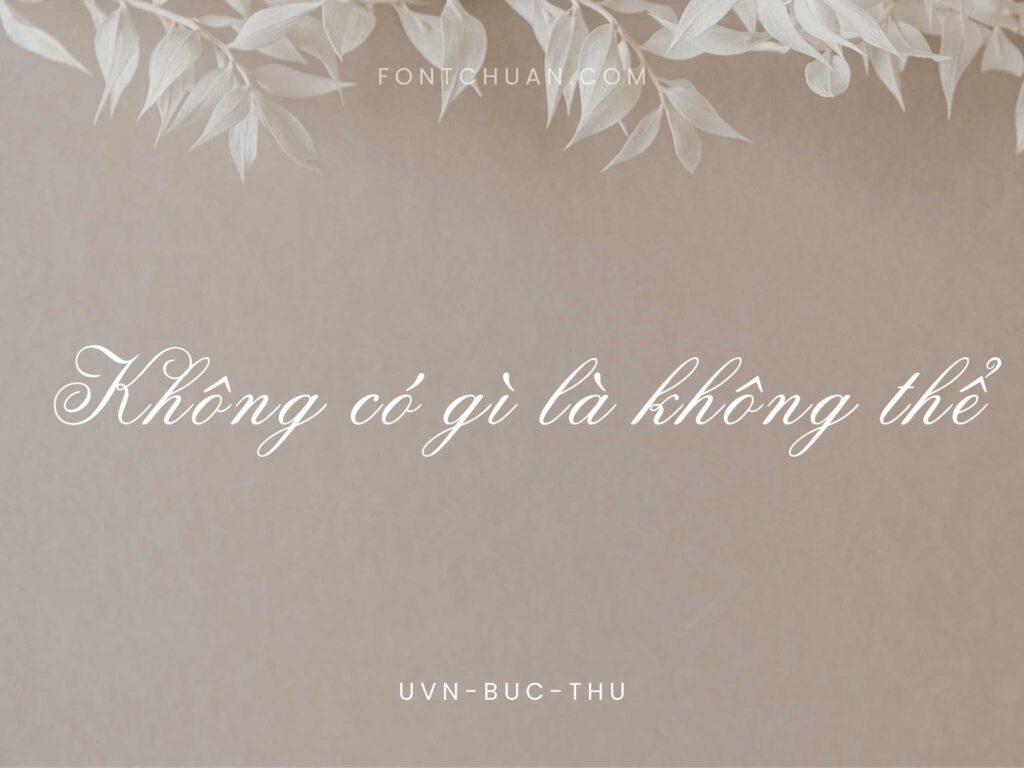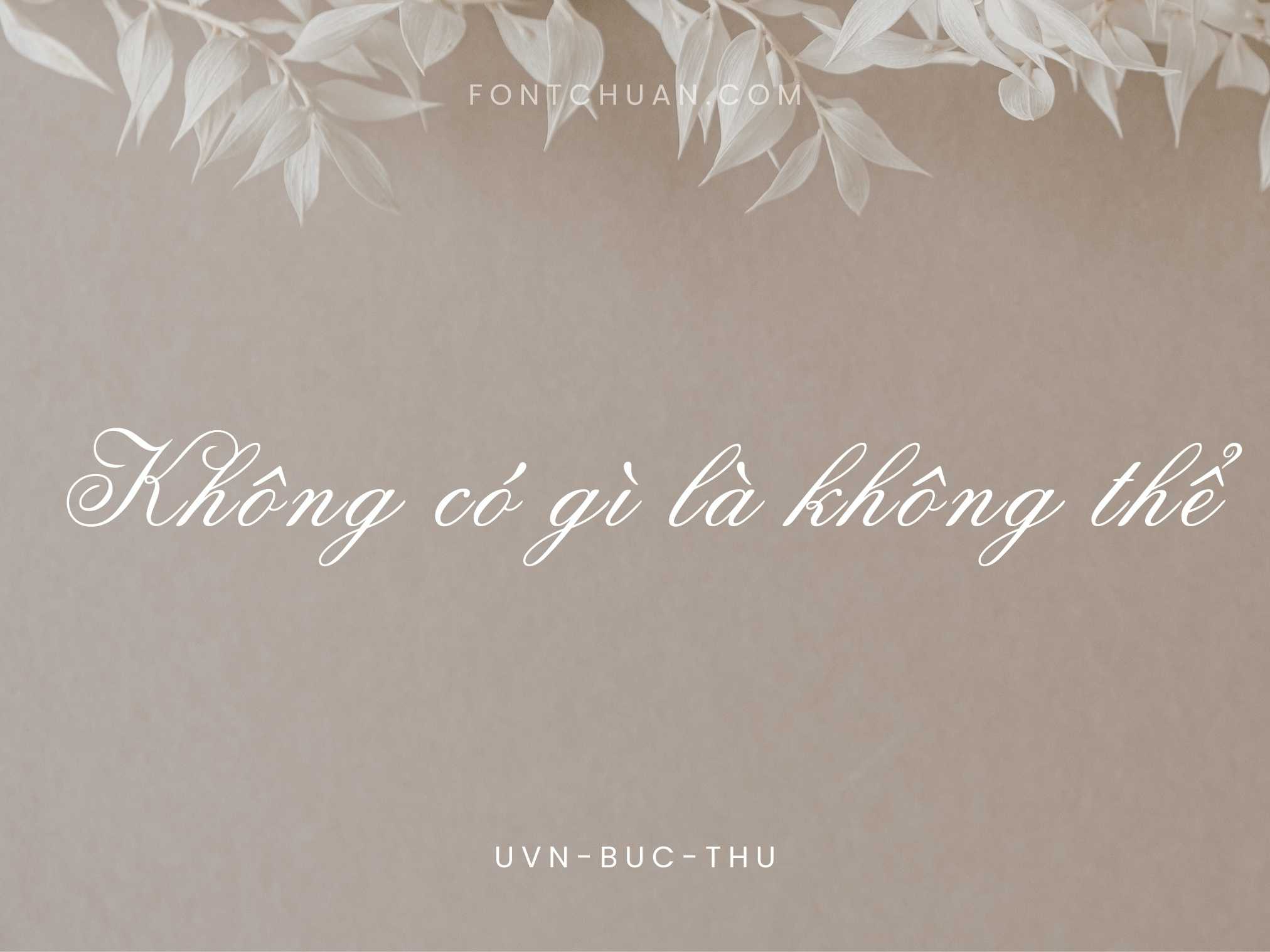
Font UVN Buc Thu Việt Hóa
UVN Bức Thư là một phông chữ script mang phong cách thư pháp, được thiết kế bởi Tom Trương vào năm 2001. Phông chữ này có các đường nét mềm mại, uyển chuyển và tinh tế, tạo nên sự trang nhã và nghệ thuật trong thiết kế. UVN Bức Thư hỗ trợ đầy đủ các ký tự tiếng Việt, giúp người dùng dễ dàng sử dụng trong các dự án sáng tạo liên quan đến văn hóa Việt Nam.
Với thiết kế độc đáo và nghệ thuật, UVN Bức Thư phù hợp cho các ứng dụng như thiệp mời, tiêu đề sách, thiết kế logo và các ấn phẩm nghệ thuật. Trong lĩnh vực sự kiện, phông chữ này có thể được sử dụng trong các dịp như lễ hội, lễ cưới và các sự kiện văn hóa. Ngoài ra, UVN Bức Thư còn là một Font chữ ảnh cưới lý tưởng, giúp trang trí thiệp cưới, album ảnh và các sản phẩm kỷ niệm, mang đến sự tinh tế, lãng mạn và sang trọng cho các thiết kế. Font này cũng phù hợp cho các ngành nghề như thiết kế đồ họa, nghệ thuật trang trí và xuất bản.